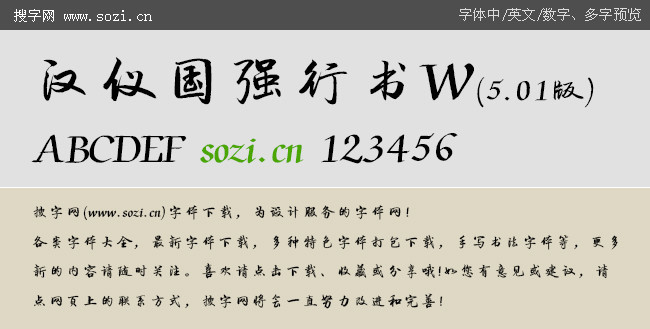
漢儀國強(qiáng)行書W5.01
搜字網(wǎng)提供一款漢儀國強(qiáng)行書W5.01中文字體下載,漢儀國強(qiáng)行書,漢儀國強(qiáng)行書字體成熟穩(wěn)重,筆鋒飄逸,俊秀美觀,整體效果非常出色,可以廣泛應(yīng)用于名片設(shè)計(jì)、新聞媒體、宣傳海報(bào)、ppt、影視制作以及內(nèi)容用字等領(lǐng)域。(本字體為個(gè)人非商用版,如需要商用請聯(lián)系漢儀公司購買版權(quán))